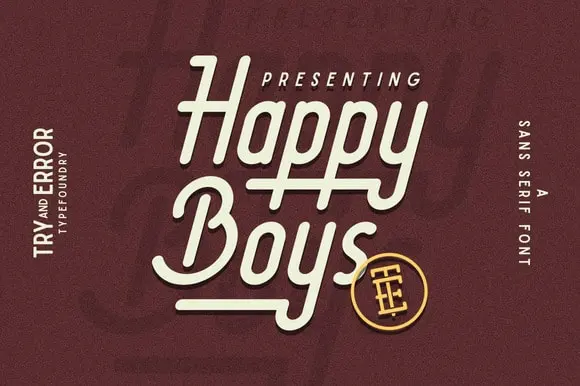
Happy Boys Typeface – Download Grátis
Introduzimos hoje a Happy Boys Typeface, uma elegante fonte de tipo linear que combina estilo moderno com sofisticação clássica. Desenhada pelo designer Angga Mahardika, esta é uma font premium disponível para download gratuito na Creativemarket. O Happy Boys oferece uma aparição fresca e natural, como se fosse feita à mão, perfeitamente adaptável a projetos diversos como cartões de aniversário, logotipos, criação de marca, cabeçalhos de websites, embalagens de produtos, desenho fashion e qualquer projeto criativo que você possa imaginar. Que tal dar uma chance a esta fonte excepcional e deixar sua próxima peça visual um pouco mais especial?